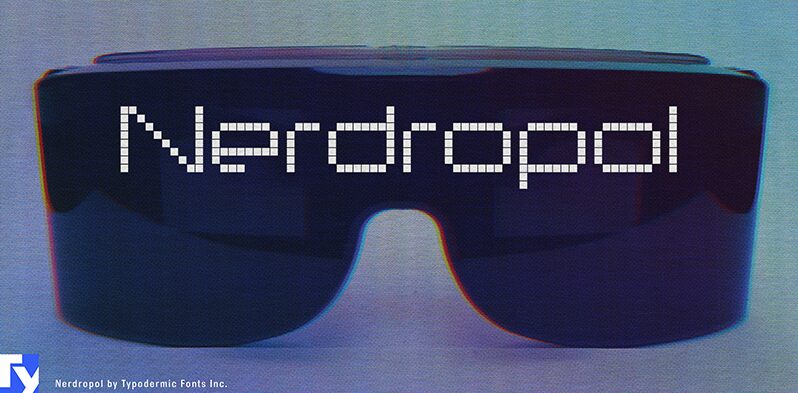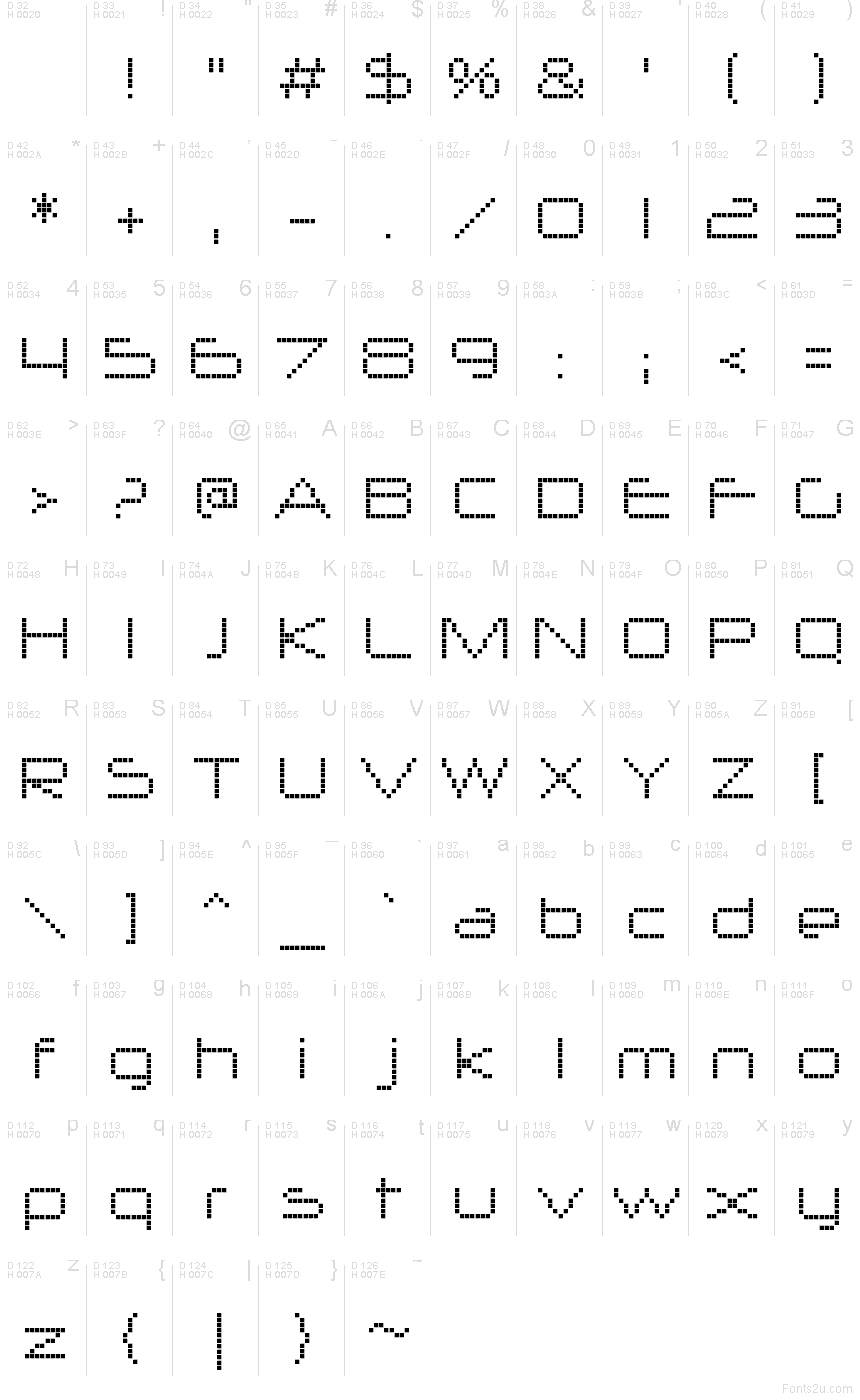
NerdropolLattice-Regular
Nerdropol je pixelové písmo postavené na prísnej mriežke, ktoré zachytáva svieži rytmus klasickej bitmapovej sadzby. Každá krivka a roh zapadá do presných dielov, čo mu dodáva nezameniteľnú štruktúru skutočnej 8-bitovej typografie.
Rôzne pixelové textúry vám umožnia prejsť od čistej arkádovej čitateľnosti k efektom mriežky alebo obrazovky, vďaka čomu je ideálne pre hernú grafiku, synthwave vizuály, technologický branding aj retro rozhrania. Nerdropol prináša autentickú pixelovú energiu do moderného dizajnu.
Ray Larabie